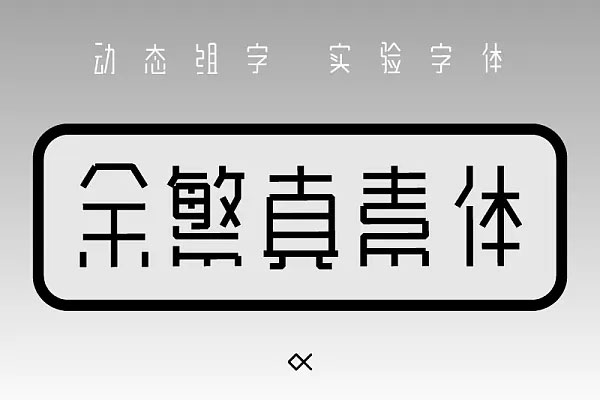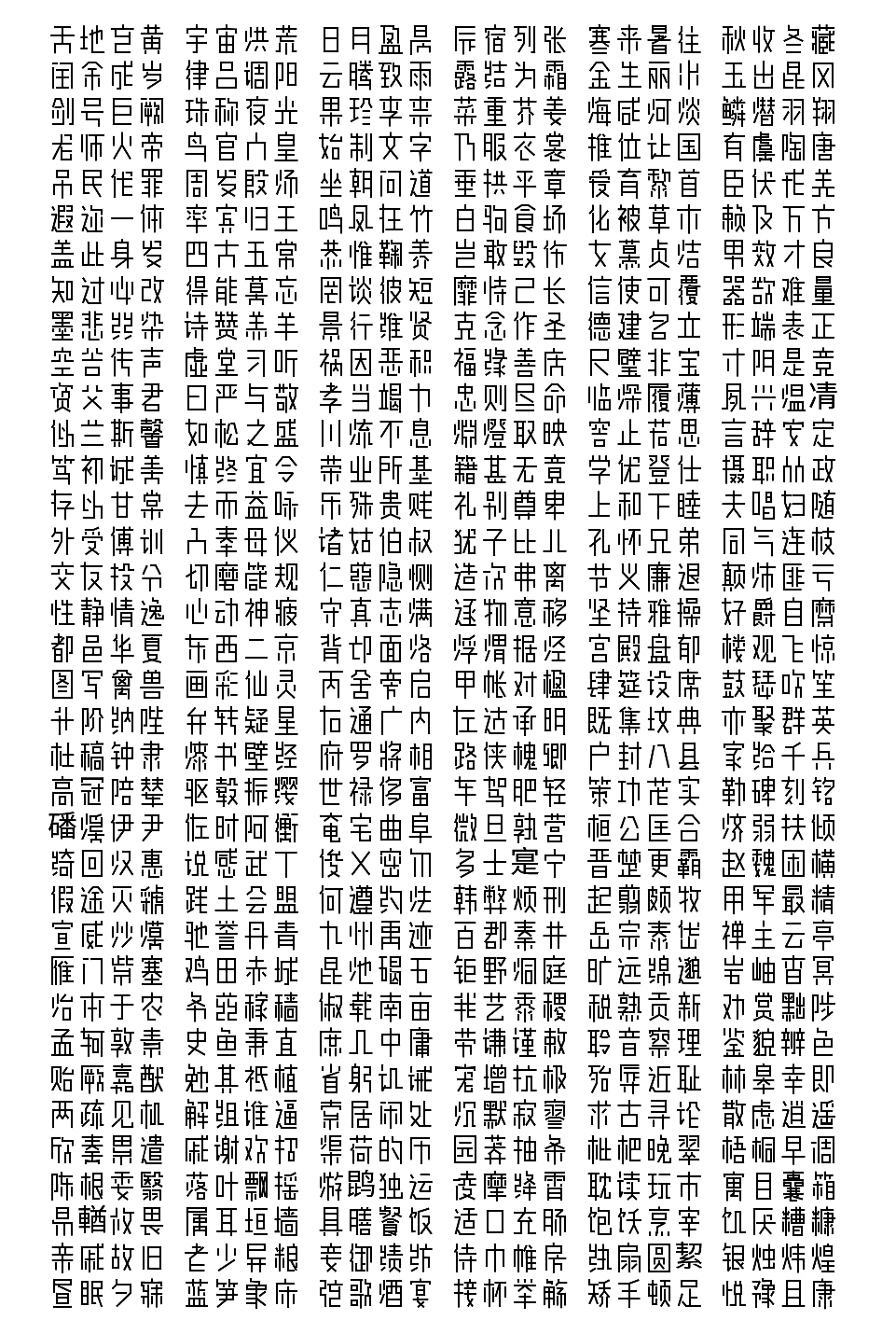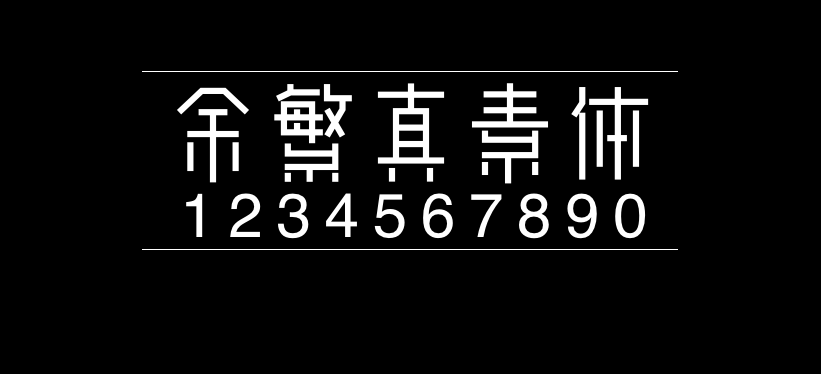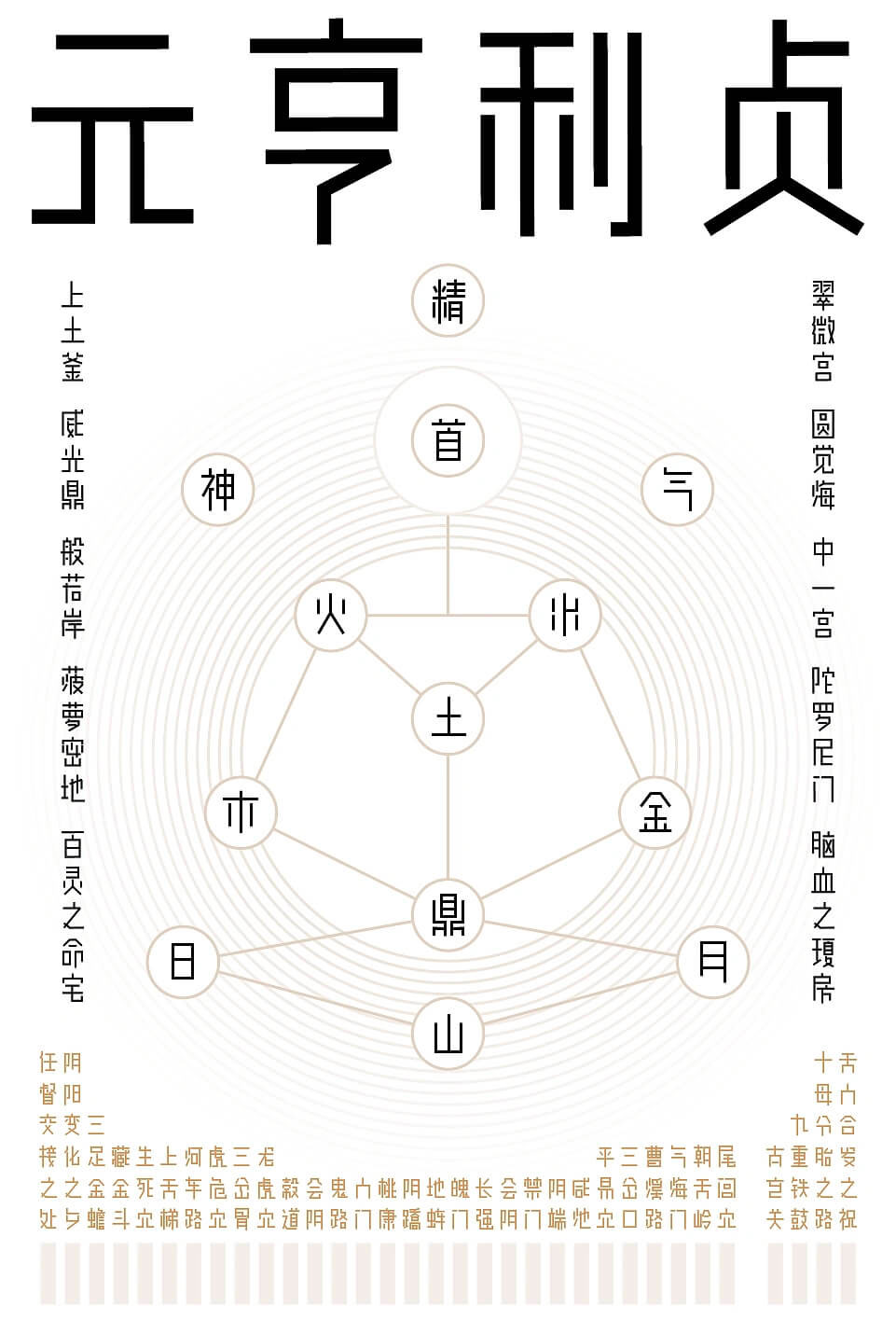
余繁真素体
余繁真素体南宁设计师余繁设计推出的一款免费商用中文字体。
以下是作者发布的原文引用:
上次说到要体系化字体的视觉平衡,花了将近四个月的时间才搞定。
现理论对于正字类字体还稍显不足,但对简单创意类字体是手拿把掐。
这个版本的真素体完全重制花了两星期,对于把一个点子拓展成一个中文字体而言,这样的时间开销勉强算是可以接受了。
写得跟数学书一样的字形平衡理论估计在站酷没几人想看,单贴点图看看具体效果哈。